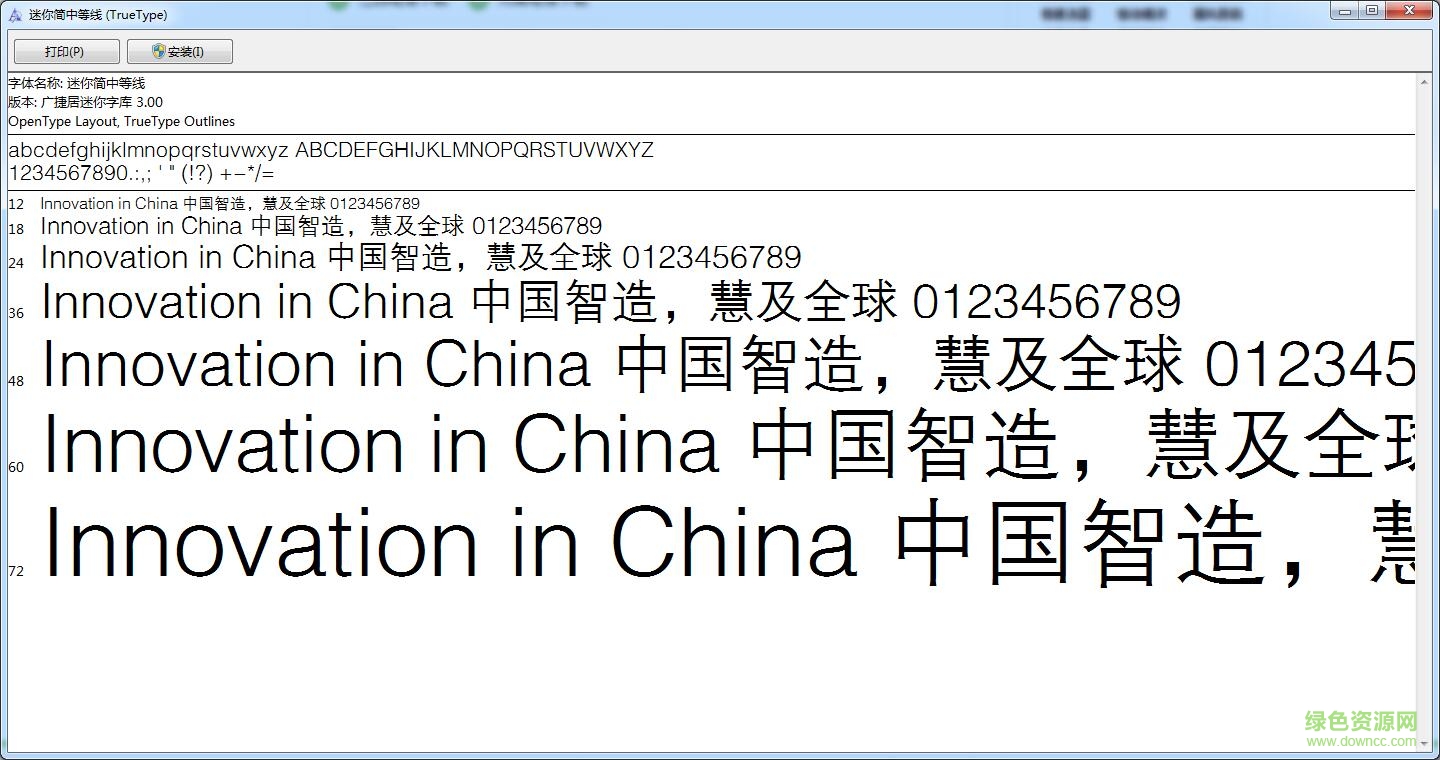
jzongdengxian
jzongdengxian字體是一款迷你簡(jiǎn)中等線,這款字體筆畫(huà)粗細(xì)勻稱十分統(tǒng)一,字型整體干凈樸素,毫無(wú)裝飾,閱讀性良好,應(yīng)用范圍廣泛,歡迎大家在綠色資源網(wǎng)下載!
等線體介紹
等線體的特點(diǎn)是都有幾乎相等的線條,前者好像漢字中的黑體,完全拋棄了字腳,只剩下字母的骨骼,顯得樸素端正,十分清晰,但過(guò)于平板,因此也叫做無(wú)字腳體!
jzongdengxian
字體分類(lèi)
襯線指的是字母結(jié)構(gòu)筆畫(huà)之外的裝飾性筆畫(huà)。有襯線的字體叫襯線字體(serif);沒(méi)有襯線的字體,則叫做無(wú)襯線字體(sans-serif)。